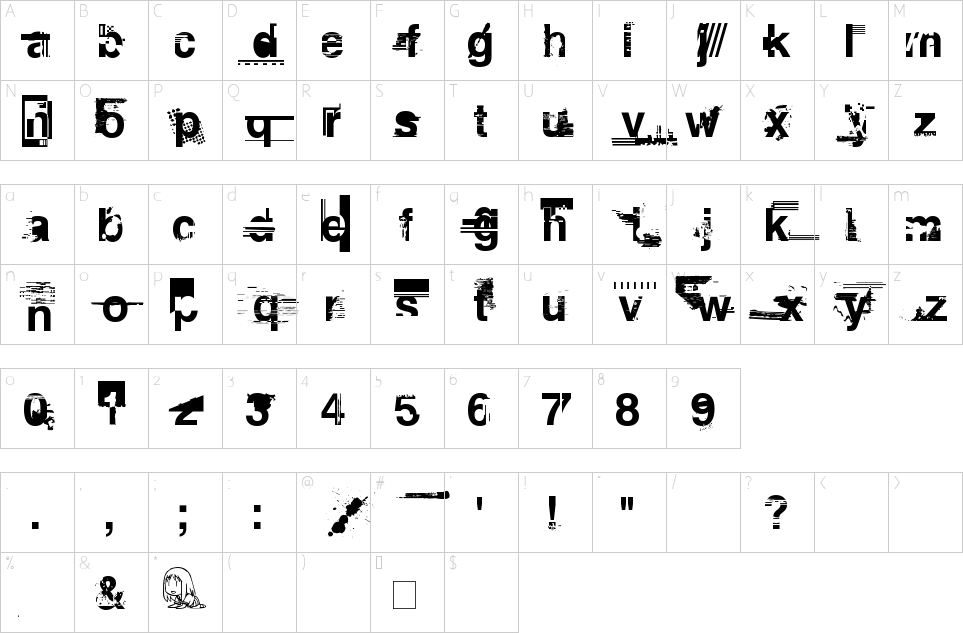
A fonte “Planned Obsolescence” para Windows e Mac é uma criação do designer Vic Fieger, disponível de graça no site 1001 Free Fonts. Esta font foi projetada para oferecer um gosto único e divertido, ideal para projetos que valorizam um tom inusitado e irreverente. Com um design inovador e colorido, a “Planned Obsolescence” é perfeita para adicionar um toque interessante a qualquer projeto, seja em design gráfico, criação de logotipos ou criação de ícones. Com a facilidade de uso de um design intuitivo, esta font é uma ótima escolha para quem procura algo diferente e divertido na biblioteca de fontes de recursos gratuitos. Desde seu lançamento, a font “Planned Obsolescence” já foi baixada por mais de 8.000 vezes, evidenciando seu valor e popularidade entre os designers e criadores de conteúdo.